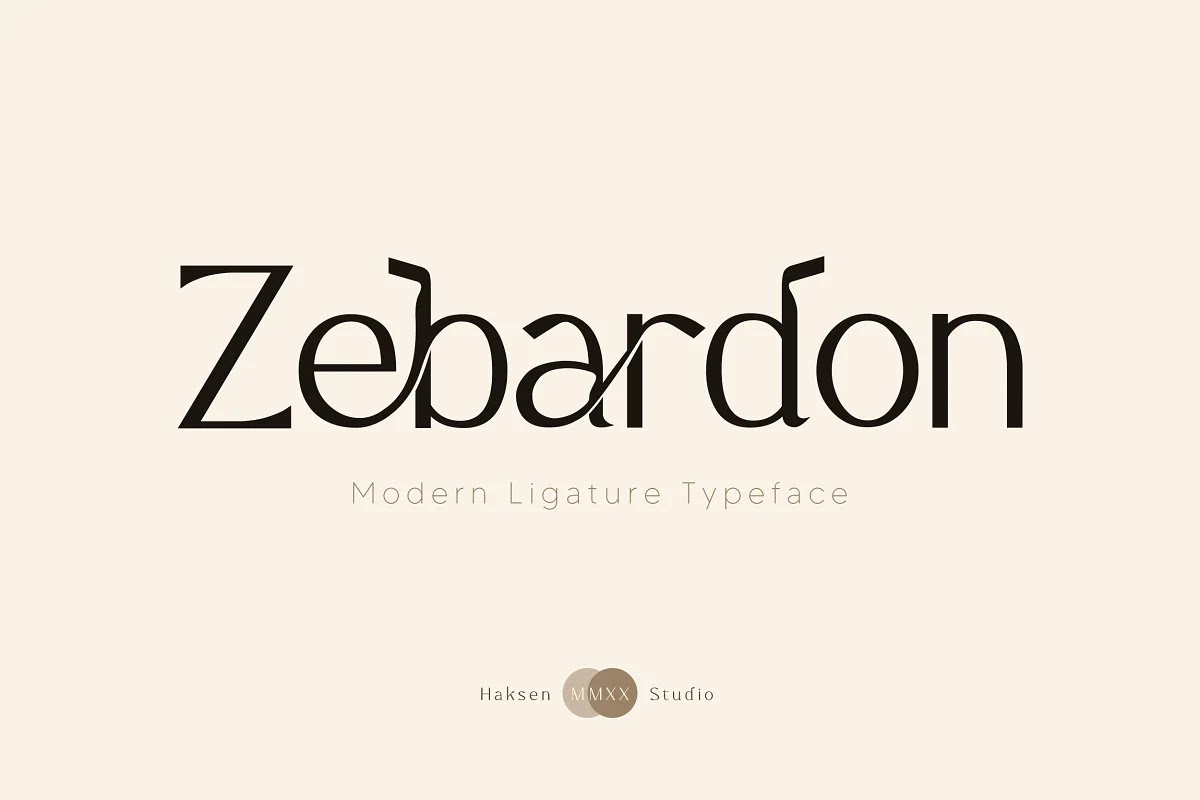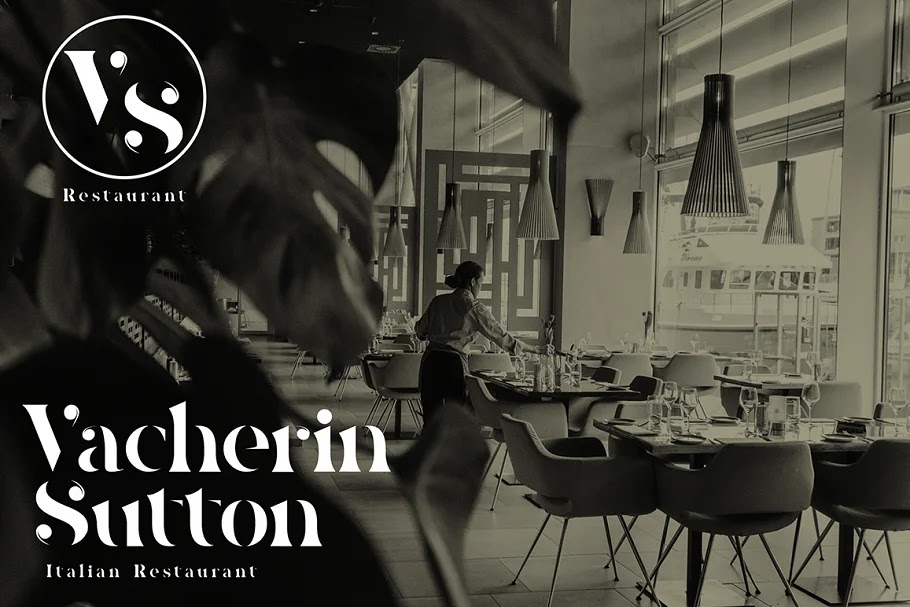
Amazing Futuristic Font Bundle 5914493 đây là bộ font chữ độc đáo với các phông chữ Serif, Sans Serif, Slab Serif và Display, tất cả đều mang phong cách hiện đại. Bao gồm 53 phông chữ tốt nhất.
Fonts Included:
- Blame
- Babylon
- Ballado
- Megatura
- Thunderboss
- Oldbrothers
- Antagonist
- Lamborte
- Tobelord
- Monsterio
- Sharon
- Nostrud
- Zebardon
- Absolute Funboldies
- Pearloop
- Carista
- Castillian